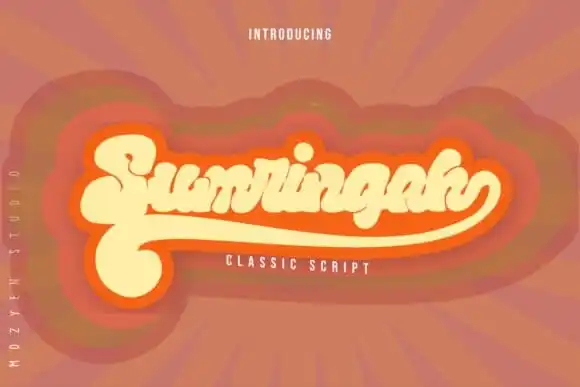
A Sumringah Script Font é uma tipografia vintage que oferece uma sensação nostálgica perfeita para os designers buscando adicionar elementos retro ou vintagem a seus projetos. Com seu design minimalista e arredondado, ela proporciona um toque de elegância clássica e modernidade atemporal à sua produção. Este tipo de fonte foi criada pela designer mozyenstudio no site 99designs. A Sumringah Script é uma fonte script bold, com seu estilo vintage marcando presença em cada letra. Perfeita para um amplo espectro de usos, desde identidades de marca e logotipos até postais e adesivos de produto, esta fonte atende a diversos requisitos visuais, tornando-a uma escolha inegável para quem deseja incorporar elementos vintage em seus projetos digitais.